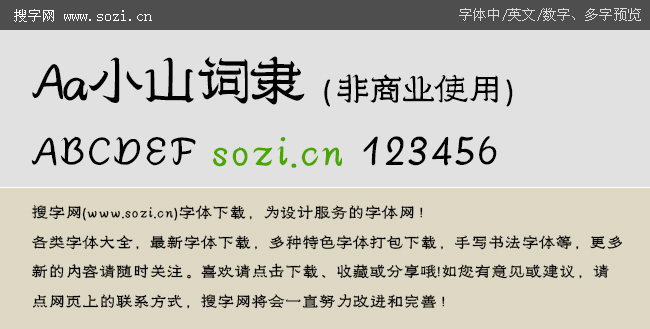
Aa小山詞隸
搜字網(wǎng)給大家提供一款A(yù)a小山詞隸(非商業(yè)使用)中文字體下載,Aa武魂體是一款藝術(shù)字體,該字體線條粗細(xì)適中,筆畫隨性,結(jié)構(gòu)肆意灑脫,具有手寫字體的藝術(shù)風(fēng)格。適合應(yīng)用于藝術(shù)設(shè)計(jì)、平面宣傳設(shè)計(jì)、網(wǎng)頁設(shè)計(jì)、海報(bào)設(shè)計(jì)等應(yīng)用(此字體為個(gè)人非商用版,商用可以聯(lián)系QQ:1006760504)。